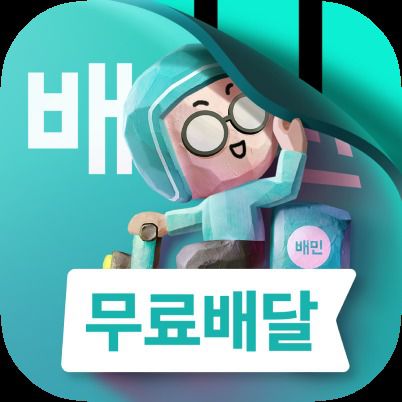
(서울=뉴스1) 윤수희 기자 = 배달의민족 운영사 ㈜우아한형제들은 배달의민족 서비스 출시 15주년을 맞아 브랜드 정체성을 새롭게 정의하는 '배민 2.0' 리브랜딩에 돌입했다고 22일 밝혔다.
먼저 디지털 환경에서 더욱 선명하고 현대적인 인상을 전달하기 위해 기존 민트 컬러보다 더욱 밝고 상쾌한 느낌의 민트색으로 브랜드 컬러를 변경했다.
또한 'WORK체'(워크체)라는 신규 폰트를 개발해 앱에 적용했다. 신규 폰트는 기존에 사용하던 한나체와 달리 심플하면서 명확한 느낌을 부각해 개발됐다. 한글의 빗침획을 블록 형태로 단순화해 배민 폰트만의 특징을 살렸다.
배민은 고객중심디자인 차원에서 전면적인 디자인 교체로 인한 이질적인 느낌을 줄이고자 여러 단계에 걸쳐 점진적으로 디자인을 리브랜딩할 예정이다.